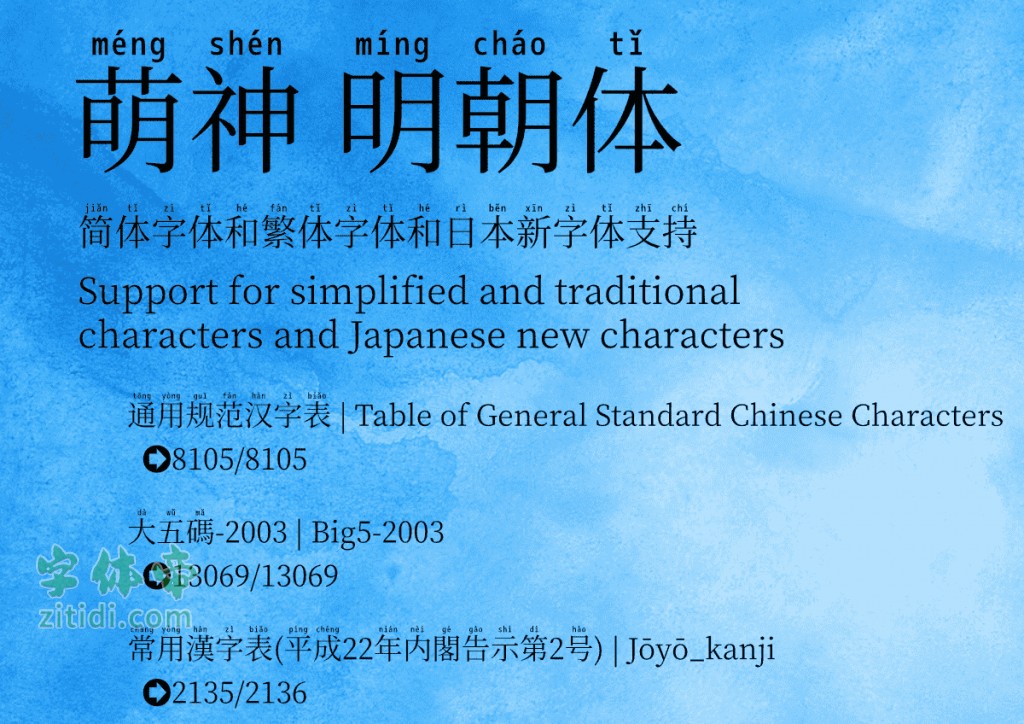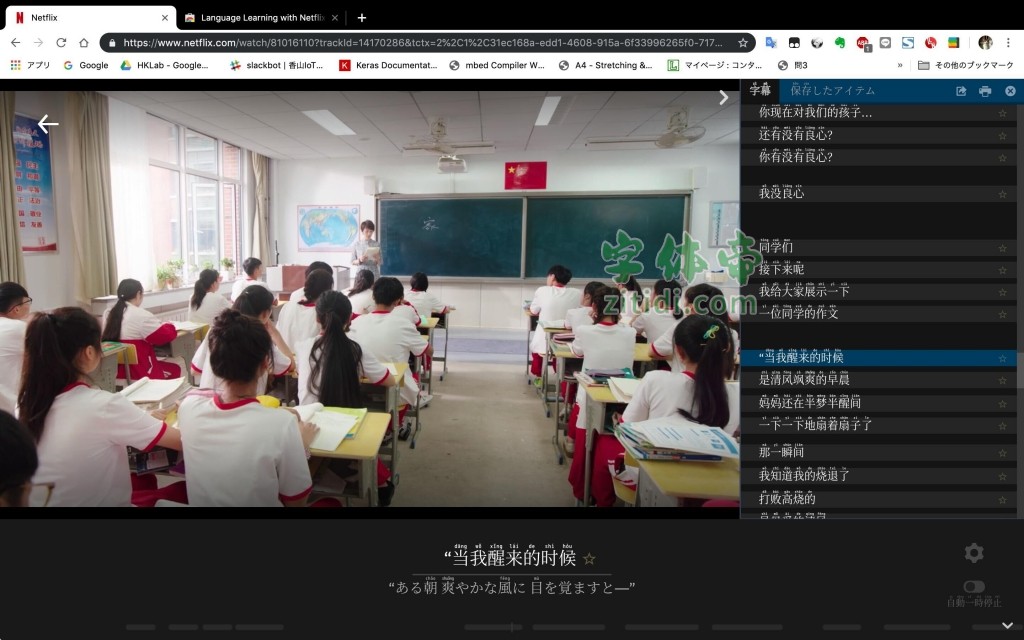
萌神拼音体
字体风格: 拼音体
萌神拼音体是用于学习中国汉字的一款字体,是使用思源宋体和M+字体进行改造而成的一款免费商用字体。 这是一种用来帮助学生更快地学习和阅读汉语的字体。在某些设计场景其实也挺实用的,特别是对教育类的设计比较有用。
基本上是可以显示日语、简体字和繁体字的字体,是在简体字和繁体字中加入拼音的字体的制作。
通过看用你所学语言制作的电影和电视剧,有效地、愉快地提高你自己的技能。字幕显示汉字和拼音。